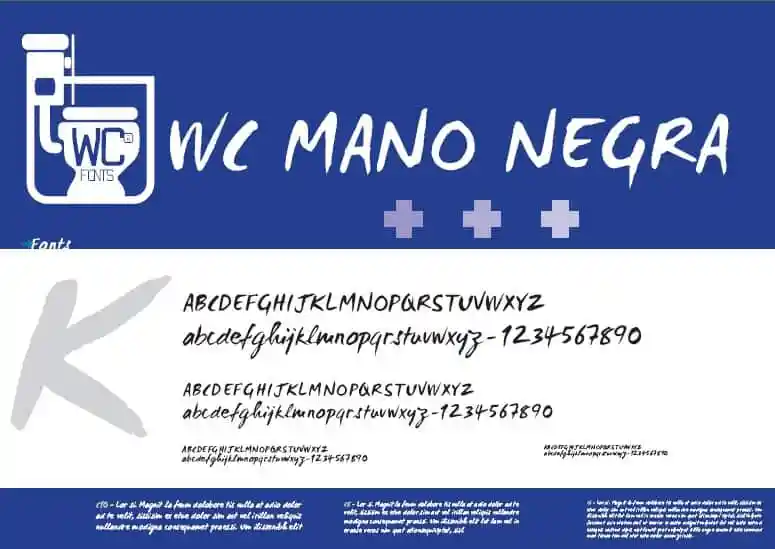
A WC Mano Negra Brush Font é uma escolha perfeita para designers que buscam personalidade e modernidade em seus projetos digitais. Desenhada pelo designer Hamilton, esta fonte brush script se destaca por suas qualidades únicas que imprimem um toque de arte na escrita digital. WC Mano Negra Brush Font é uma escolha ideal para quem quer transmitir a sua identidade visual de maneira única e expressiva. Suas linhas fortes e curvas suaves, combinadas com o estilo único da fonte, criam um efeito imediatamente impactante. Seja no design de seu website, suas redes sociais ou até mesmo nos seus banners do Pinterest, a WC Mano Negra Brush Font adiciona uma personalidade única que cativa sua audiência, clientes e convidados. Através da WC Mano Negra Brush Font, você pode inspirar os outros, especialmente em seu público-alvo. Esta fonte é mais do que apenas um recurso gráfico; ela é uma maneira de transmitir a sua personalidade e estilo visual com clareza. Eles podem não entender o design impresso, mas certamente perceberão o significado e a essência da sua mensagem através desta fonte poderosa e única. Inspirada nos estilos das letras manuscritas e desenhadas à mão, esta é uma excelente escolha para qualquer projeto que deseja transmitir personalidade com elegância. A WC Mano Negra Brush Font traz um ar de originalidade aos seus projetos digitais, tornando-os ainda mais memoráveis e cativantes.